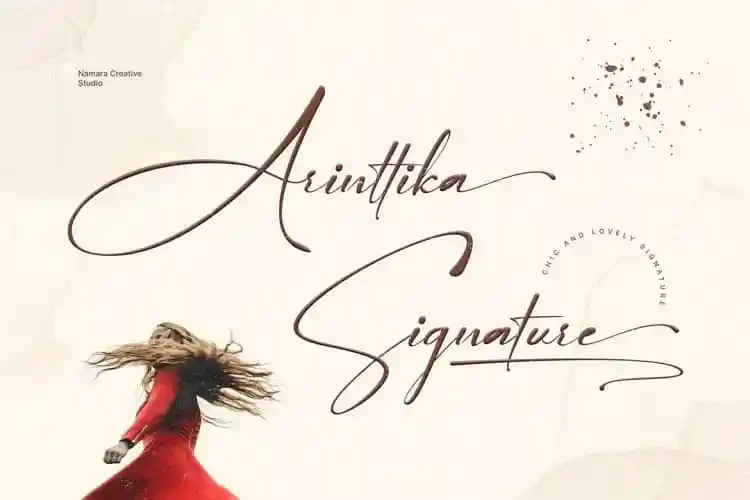
Arinttika Script Font – Download Grátis
Arinttika Script Font é uma elegante fonte escrita à mão criada pelo Namara Creative Studio. Com seu aspecto delicado e fluido, ela transmite a essência de um espírito refinado. Perfeita para uma ampla gama de projetos, desde identidades corporativas e convites até embalagens de produtos e marcas de marca. Seu uso é extremamente versátil, ideal para diversos aplicativos, como logotipos e identidade visual, cartões de visita, materiais de decoração, designs de casamentos, posts nas redes sociais, anúncios publicitários, embalagens de produtos, etiquetas, fotografia e até mesmo marcas de água. A fonte inclui letras maiúsculas e minúsculas, swashes (cargas), números, pontuação, suporte para múltiplas línguas e alternativas para as letras minúsculas com swashes no final. Essa é uma fonte que se destaca por sua versatilidade e elegância, perfeita para projetos de design criativos.